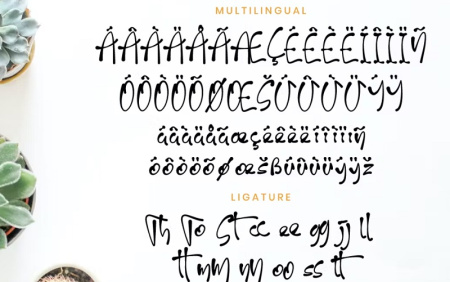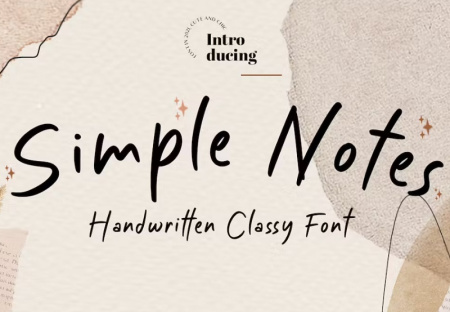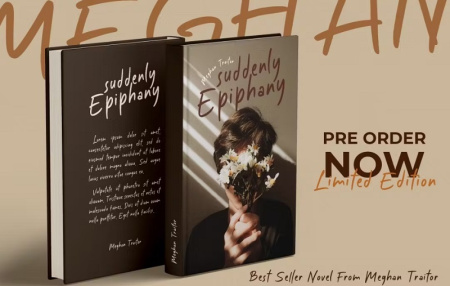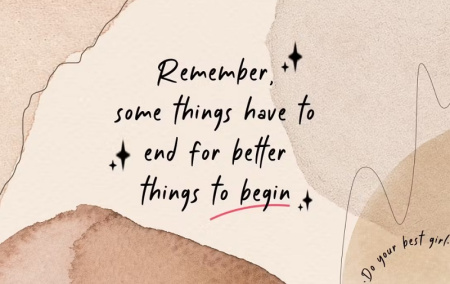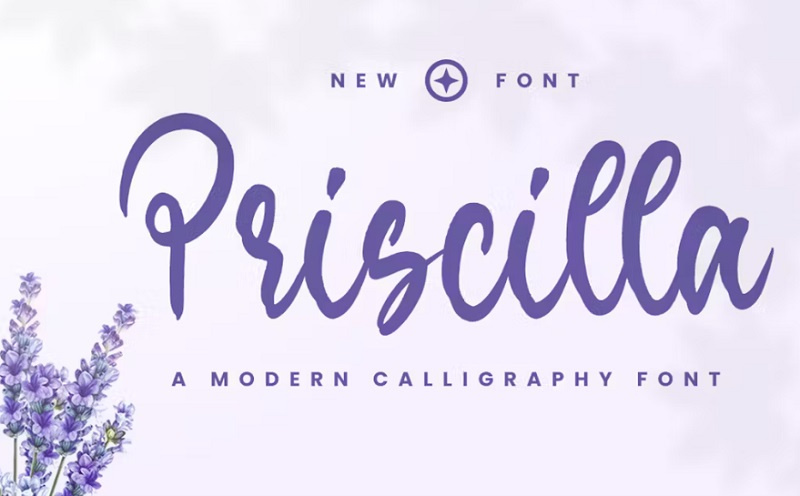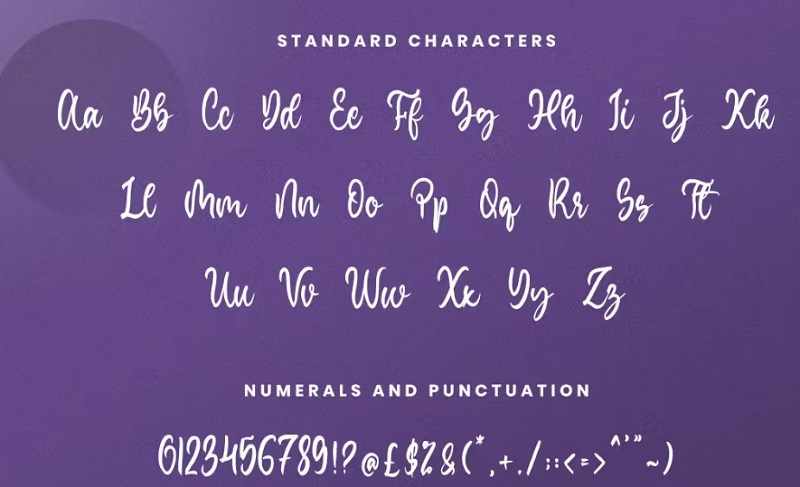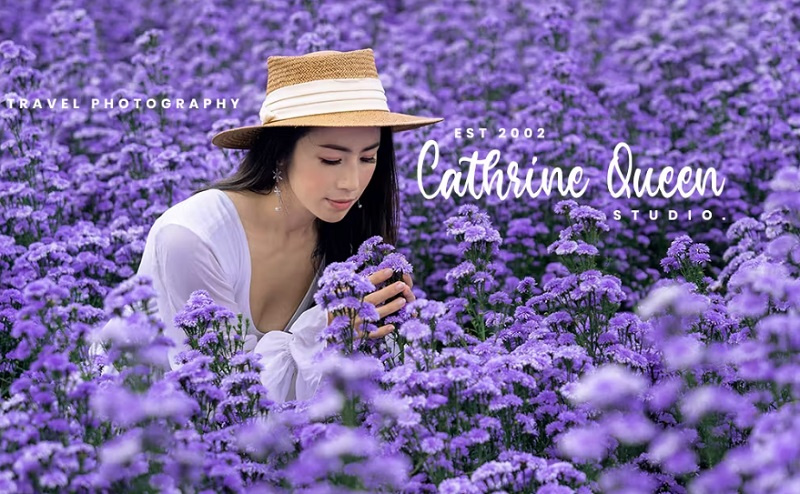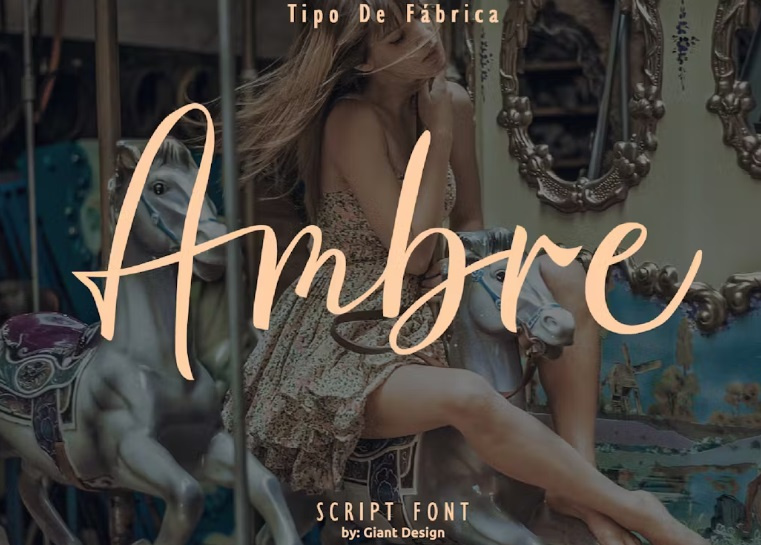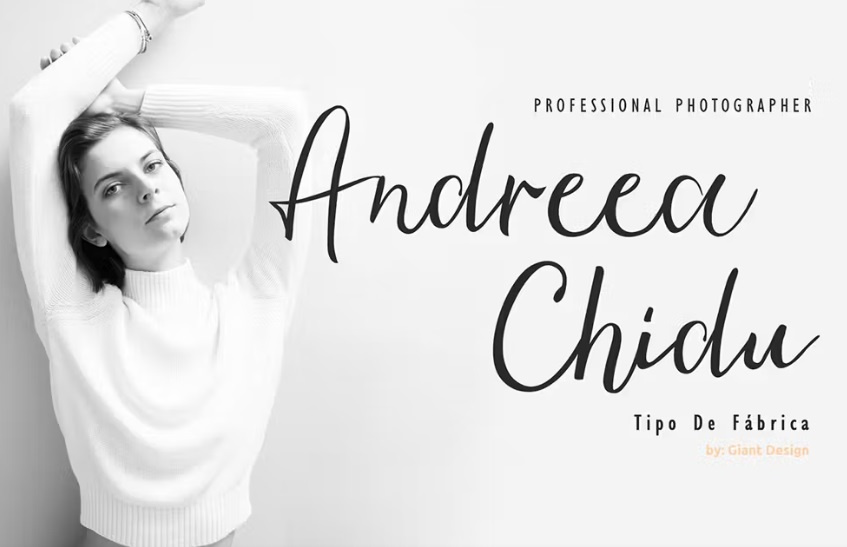
فونت انگلیسی برای استوری Story Basty آپدیت جدید 2026
فونت انگلیسی برای استوری
فونت انگلیسی برای استوری شامل 5 فونت با سبک دست نوشته زیبا می باشد که میتوانید برای استوری های اینستاگرام و سایر شبکه های اجتماعی از آن استفاده کنید. همچنین این فونت انگلیسی استوری برای برچسب، عکاسی، واترمارک، دعوت نامه، لوازم التحریر، پروژه های برندسازی، لوگو، طرح های عروسی، پست های رسانه های اجتماعی، تبلیغات، بسته بندی محصول، طراحی محصول، بازاریابی دیجیتال، ویدئو بسیار مناسب است. در ادامه می توانید تصاویر این فونت های زیبا را از جی اف ایکس دانلود مشاهده نمایید.
1- دانلود فونت انگلیسی استوری Story Basty
داشتن این فونت یکی از ضروری ترین مواردی هست که برای دیده شدن در شبکه های اجتماعی مثل اینستاگرام نیاز دارید. این فونت انگلیسی استوری حالت دست نوشته و بسیار زیبا دارد. در ادامه تصاویر این فونت زیبا را می توانید مشاهده نمایید.
2- فونت انگلیسی استوری اینستاگرام Simple Notes
Simple Notes یک فونت اسکریپت نازک، ظریف و لاکچری برای رسانه های اجتماعی، به ویژه برای اینستاگرام است. از فونت انگلیسی استوری اینستاگرام می توانید برای ایجاد دعوت نامه های عروسی زرق و برق دار، هنرهای ثابت زیبا، پست های رسانه های اجتماعی چشم نواز و موارد دیگر استفاده کنید!
3- فونت انگلیسی استوری Priscilla
Priscilla یک فونت بسیار زیبا مخصوص استوری های اینستاگرام است. این فونت ظاهری شیک و مدرن دارد که می تواند برای لوگوها، برندسازی، دعوت نامه ها، لوازم التحریر، طرح های عروسی، پست و استوری های اینستاگرام و موارد دیگر استفاده شود.
4- فونت انگلیسی مخصوص استوری Ambre
Ambre یک فونت انگلیسی برای استوری های اینستاگرام و سایر طراحی های گرافیکی می باشد. مناسب برای استوری های اینستاگرام، معرفی محصولات طبیعی، برندسازی، لوگو، طرح های عروسی، پست های رسانه های اجتماعی، تبلیغات، بسته بندی محصول، طراحی تیشرت، عکاسی، واترمارک، دعوت نامه، لوازم التحریر و هر پروژه ای عالی است.
5- فونت انگلیسی شیک برای استوری اینستاگرام + متن‌های زیبا برای بیو
اگر به دنبال فونت انگلیسی استوری اینستاگرام هستید و می‌ خواهید استوری‌ ها، بیو و محتوای پیج خود را متفاوت‌ تر و جذاب‌ تر کنید، این فونت‌ انگلیسی زیبا و کاربردی با نام Pen Story می‌ تواند انتخاب مناسبی باشد. در این مطلب می‌ توانید فونت‌ هایی با سبک‌ های فانتزی، مینیمال، دست‌ نویس، ظریف و مدرن پیدا کنید که برای طراحی استوری، نوشتن متن روی عکس، ساخت کاور و استفاده در بیو کاربرد دارند. همچنین اگر به دنبال متن انگلیسی زیبا برای بیو و استوری اینستاگرام هستید، استفاده از این فونت انگلیسی خاص برای بیو و استوری اینستاگرام مناسب می‌ تواند ظاهر نوشته‌ ها را جذاب‌ تر و حرفه‌ ای‌ تر نشان دهد. با دانلود فونت‌ های انگلیسی از جی اف ایکس دانلود، می‌ توانید برای تولید محتوای اینستاگرام، طراحی پست و استوری و ساخت نوشته‌ های خلاقانه، گزینه‌ های متنوعی در اختیار داشته باشید.
ویژگی های دانلود فونت انگلیسی برای استوری های اینستاگرام
✅ نام فونت انگلیسی1: Story Basty
✅ نام فونت انگلیسی2: Simple Notes
✅ نام فونت انگلیسی3: Priscilla
✅ نام فونت انگلیسی4: Ambre
✅ نام فونت انگلیسی5: Pen Story
✅ شامل مجموعه ای کامل از حروف بزرگ و کوچک
✅ پشتیبانی چند زبانه
✅ شامل اعداد، علائم نقطه گذاری، لیگاتورها